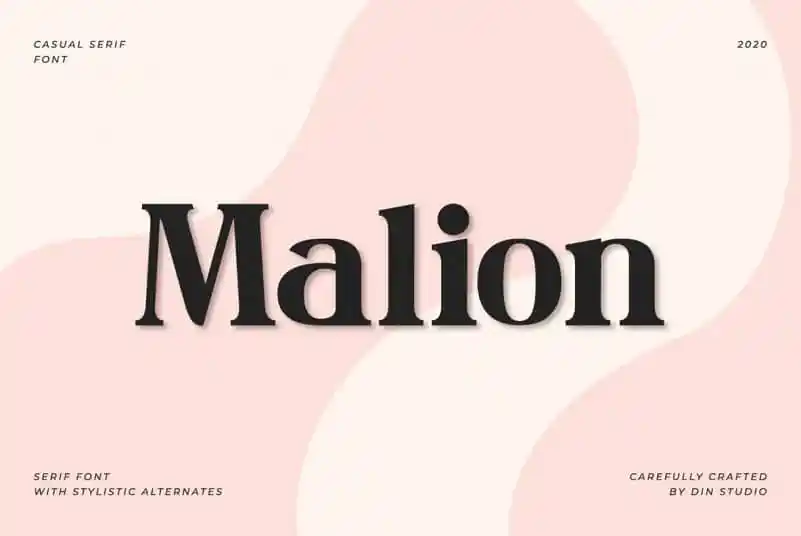
Malion Serif Font – Download Grátis
A Malion Serif é uma nova opção para os designers que buscam uma serif moderna e única. Desenvolvida pela Din Studio na plataforma 99designs, esta fonte foi criada para perfis de texto grandes, logotipos, criações visuais e qualquer tipo de projeto impresso ou digital. Sua estrutura fluida e elegante permite que você crie designs mais belos e inspiradores sem esforço. A Malion Serif é perfeita para criar um olhar clássico e sofisticado em qualquer projetos, seja para o branding da sua marca, a criação de uma template impressa ou até mesmo para personalizar seu logotipo. Desenvolvida por fontes talentosas na Din Studio, esta fonte é um verdadeiro complemento a um design, tornando-o ainda mais sofisticado e atraente. Experimente e descubra por si só o potencial desta fonte única.